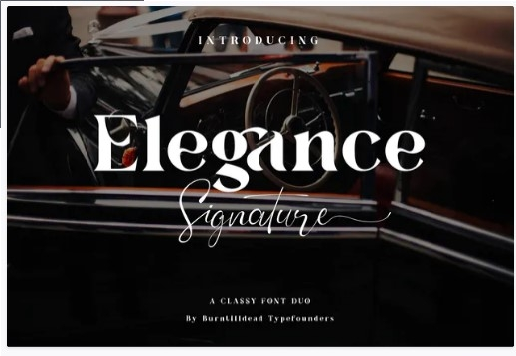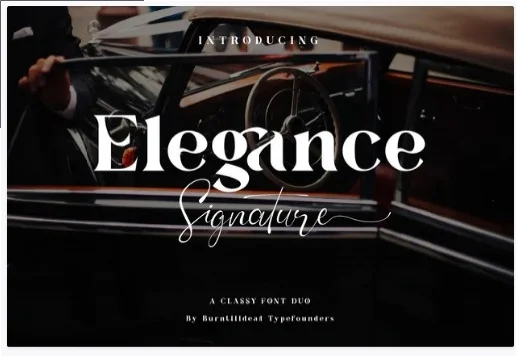
[Elements.Envato] Elegance Signature Font (2021)
Представляем "Elegance Signature" - стильное сочетание шрифта с засечками и шрифта со шрифтом. Идеальный шрифтовой дуэт с современным стильным видом шрифта с засечками в сочетании со свободно текущим шрифтом подписи. Имеет функции открытого шрифта, альтернативные символы и лигатуры. Кодировка PUA.
Легко использовать для ваших дизайнерских проектов, включая логотипы, брендинг, свадебные дизайны, посты в социальных сетях, рекламу и дизайн продукции.
Особенности:
Набор символов A-Z
Набор символов a-z
Цифры и пунктуация (стандарт OpenType)
лигатуры
Альтернативные символы
Многоязычный